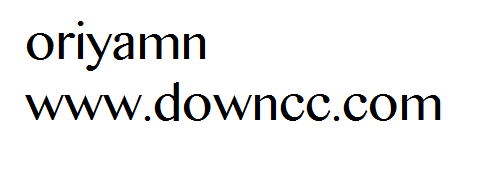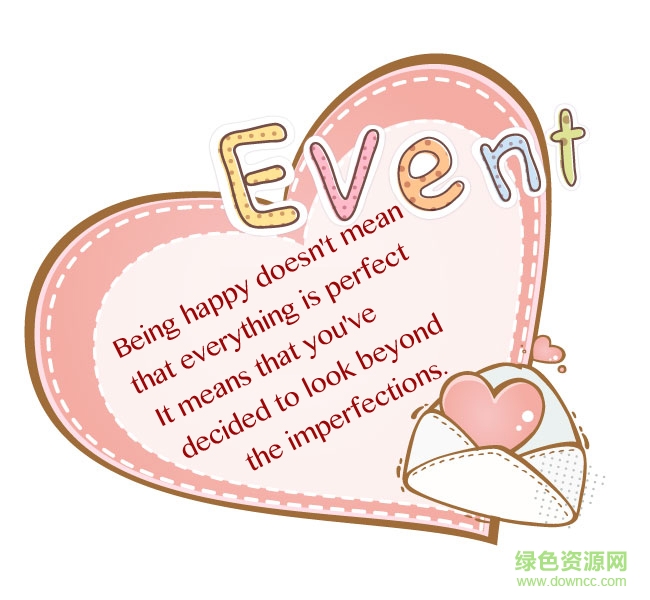
oriyamn英文字體
oriyamn字體是一款英文字體軟件,因?yàn)槠湔w特點(diǎn)比較浪漫可愛,在英文設(shè)計(jì)方面有著不錯(cuò)的應(yīng)用,更多類似好看字體盡在綠色資源網(wǎng)!
oriyamn英文字體介紹
oriyamn字體
小編點(diǎn)評(píng)
oriyamn字體筆畫不拘一格,給人清新脫俗的感覺,十分好看迷人,綠色資源網(wǎng)為您提供綠色免費(fèi)的oriyamn字體下載!